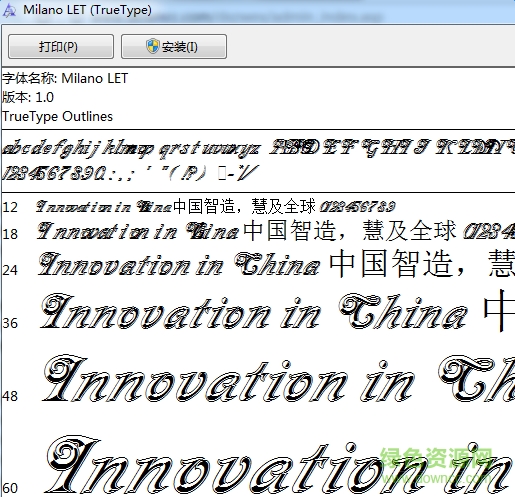
milano英文字體
milano字體是一款英文字體庫(kù)中的個(gè)性字體,該字體以其飄逸個(gè)性,讓許多設(shè)計(jì)行業(yè)的用戶深有體會(huì),有需要的朋友可以免費(fèi)下載收藏。
milano字體是一款極具個(gè)性的字體,該字體十分飄逸,彰顯了自己的個(gè)性,有喜歡的朋友可以來綠色資源網(wǎng)下載使用!